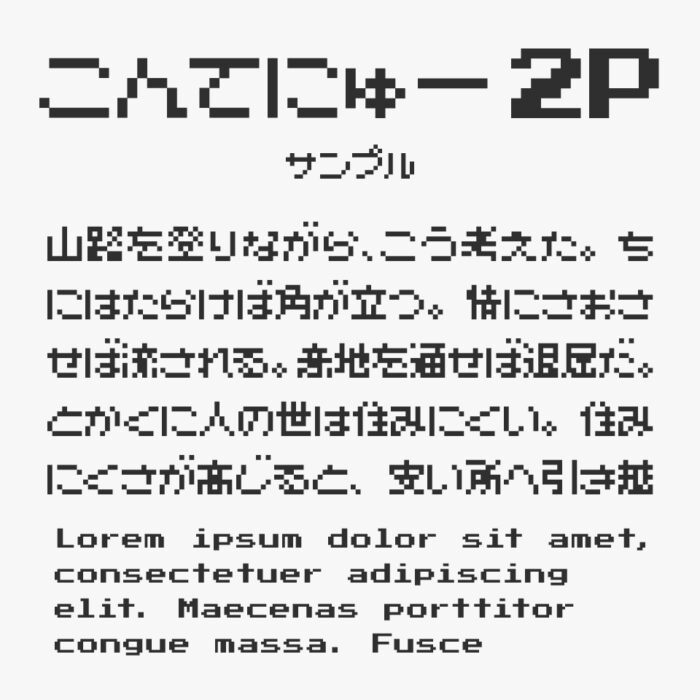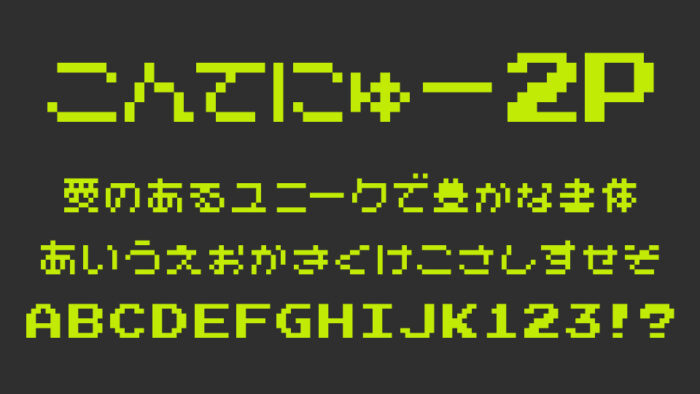
こんてにゅー 2Pフォントは、レトロゲームを思わせるようなドット調のデザインで、平体のように縦が短めに作られたのが特徴なドットフォントです。
7×7のサイズを基本して、オリジナルのかな文字は縦サイズが短めに作られていることで、レトロっぽさがあり、可愛さらしさを感じるフォントデザインとなっています。
漢字には「美咲ゴシック」、英数字には「Press Start 2P」が合成されています。
| 漢字 | ○(JIS第1・2水準まで収録) |